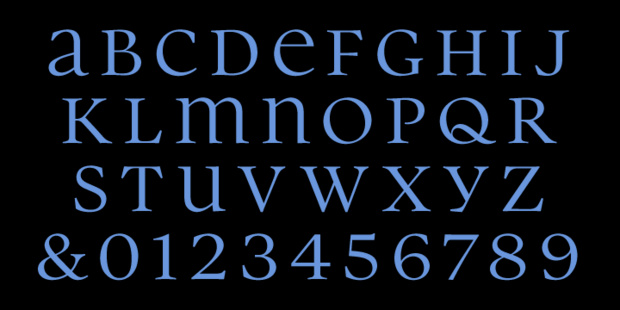
Unikameral - die neue Übersetzung für Unicase?
Gerade hat Nick Shinn seine Parity veröffentlicht – eine Schrift, die von Grund auf als Unicase-Schrift, also als Kombination von Groß- und Kleinbuchstabenformen mit gleicher Buchstabenhöhe, gestaltet wurde.
Doch wie soll man Schriften dieser Art eigentlich im Deutschen bezeichnen? Dies fragte sich auch Jürgen Siebert von FontShop Deutschland. Die FontBook App ist mehrsprachig angelegt, aber eine Übersetzung für Unicase innerhalb dieser Anwendung fehlte bislang. Siebert fragte daher auf Twitter nach einer Übersetzung. Einen etablierten Begriff scheint es nicht zu geben, aber schnell wurden von verschiedenen Seiten neue Kunstwörter als Vorschlag unterbreitet; zum Beispiel Miscuskel/Mixuskel, Mononuskel/Monuskel oder Binuskel.
• Den bislang überzeugendsten Vorschlag lieferte schließlich Florian Hardwig:
HEIM bzw. heim -> monokameral
Heim -> bikameral
HҼУM -> unikameral
Im Gegensatz zu den anderen Vorschlägen wird hier kein völlig neues Wort erfunden, da der sprachliche Bezug auf die zwei »Kammern« der lateinischen Schrift so bereits in anderen Sprachen im Einsatz ist. So findet sich bicameral/bicamérale zum Beispiel im Englischen und im Französischen.
Wir möchten diesen Vorschlag zur Etablierung von unikameral als deutsche Übersetzung für Unicase gern unterstützen und einen entsprechenden Artikel im Wiki von Typografie.info anlegen. Zuvor möchten wir jedoch der Community von Typografie.info noch einmal die Chance geben, über diesen Vorschlag zu diskutieren.
(Alle gezeigten Schriftmuster: Parity von Nick Shinn)